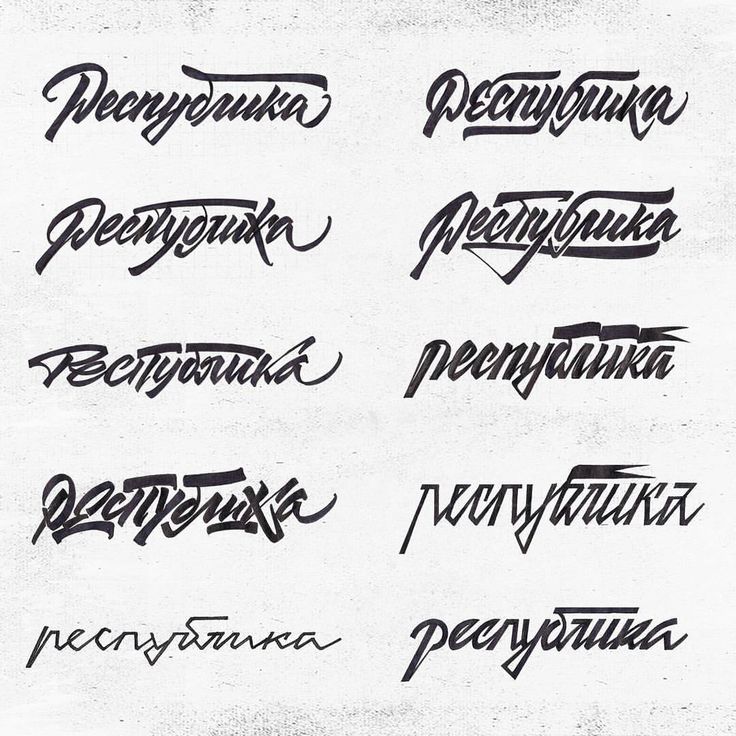
Русские шрифты для журнала. Лучшие бесплатные шрифты для дизайнеров
Сейчас самое время повышать уровень дизайна своих работ с помощью веб-шрифтов
Без преувеличения, сейчас сетевая типографика переживает захватывающий период своей жизни. Недавние технологические скачки приблизили нас еще на шаг ближе к типографической нирване в интернете. Шаг, которого все так долго ждали.
Свобода использования веб-шрифтов вне безопасного списка на всех ведущих ОС стала возможной, по большому счету, благодаря трем основным, почти одновременным технологическим факторам: широко распространенной поддержке правила @font-face в браузерах; появлению таких «шрифтохранилищ» как Typekit и Fontdeck ; создание нового формата шрифтов — архивированного файла шрифта WOFF.
* Мало что из этих шрифтов есть для кириллицы, поэтому эта подборка больше подойдет для «аутсорсеров». Будем надеятся, что скоро появится хоть часть этих и не только шрифтов для славянских языков на кириллице.
Шфриты в веб-дизайне вещь практически незаменимая. Используя при разработке дизайна сайта нестандартные и оригинальные шрифты вы можете достичь поистине удивительного результата. Разработка баннеров, иллюстраций, разного рода афиш и других нестандартных текстово-графических материалов без специальных шрифтов и вовсе невозможна. В данном разделе блога вы найдете разные англоязычные и русские кириллические шрифты для фотошопа и сможете понравившиеся вам экземпляры шрифтов скачать бесплатно.
Все материалы разделены и скомпонованы в отдельные наборы по тем или иным тематикам — каллиграфические, готические, новогодние, оригинальные, рукописные и многие другие шрифты к вашим услугам. Я постараюсь отобрать и найти самые лучшие наборы шрифтов в интернете для публикации в Дизайн Маним. Постараюсь, чтобы вы могли скачать шрифты для фотошопа которые действительно пригодятся в работе, а не просто пополнят вашу и без того большую коллекцию шрифтов.
Подобный вариант с декоративным шрифтом надписи мелом также неплохо будет смотреться в полиграфии. Где бы вы его не применили, подборка ниже окажется полезной. Всего собрали около 50-ти объектов на любой вкус. Перед тем,…
По случаю наступившей зимы мы решили подготовить тематическую заметку про зимние шрифты. Года два назад в Дизайн Мании уже были публикации о новогодних и рождественских шрифтах, однако там собраны далеко не все интересные варианты + за пару лет появились новые работы. Уверены, в статье ниже найдете парочку полезных решений. В свою очередь мы проследим чтобы в данной и предыдущих подборках объекты не повторялись. В посте…
Если вы начнете искать размытые шрифты для фотошопа в сети, то увидите, что большинство ссылок из выдачи ведут на совсем другие публикации. В основном пользователи ищут как исправить проблему нечетких шрифтов в браузере или windows на своем компьютере. Поэтому дабы упростить вам процесс поиска лучших и самых необычных размытых шрифтов для графики и иллюстраций мы сделали соответствующую подборку.
Данные материалы могут применяться для разного рода постеров и афиш. В принципе,…